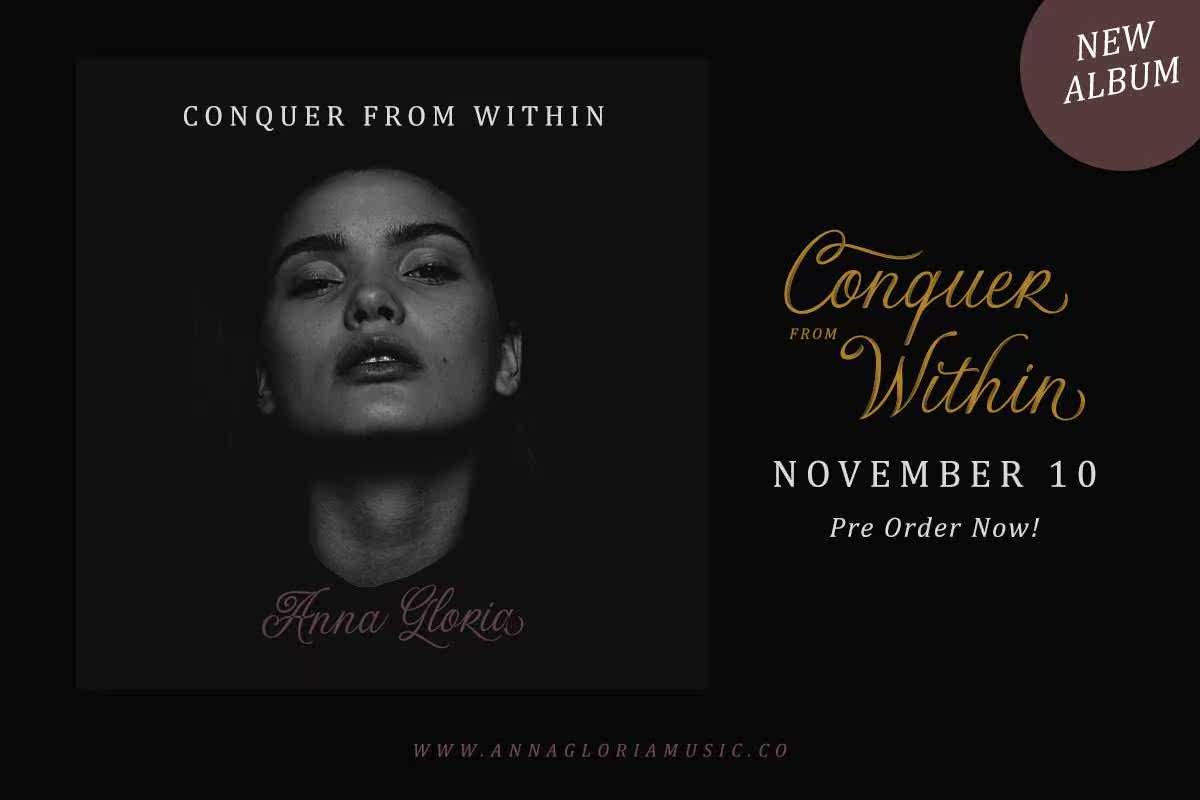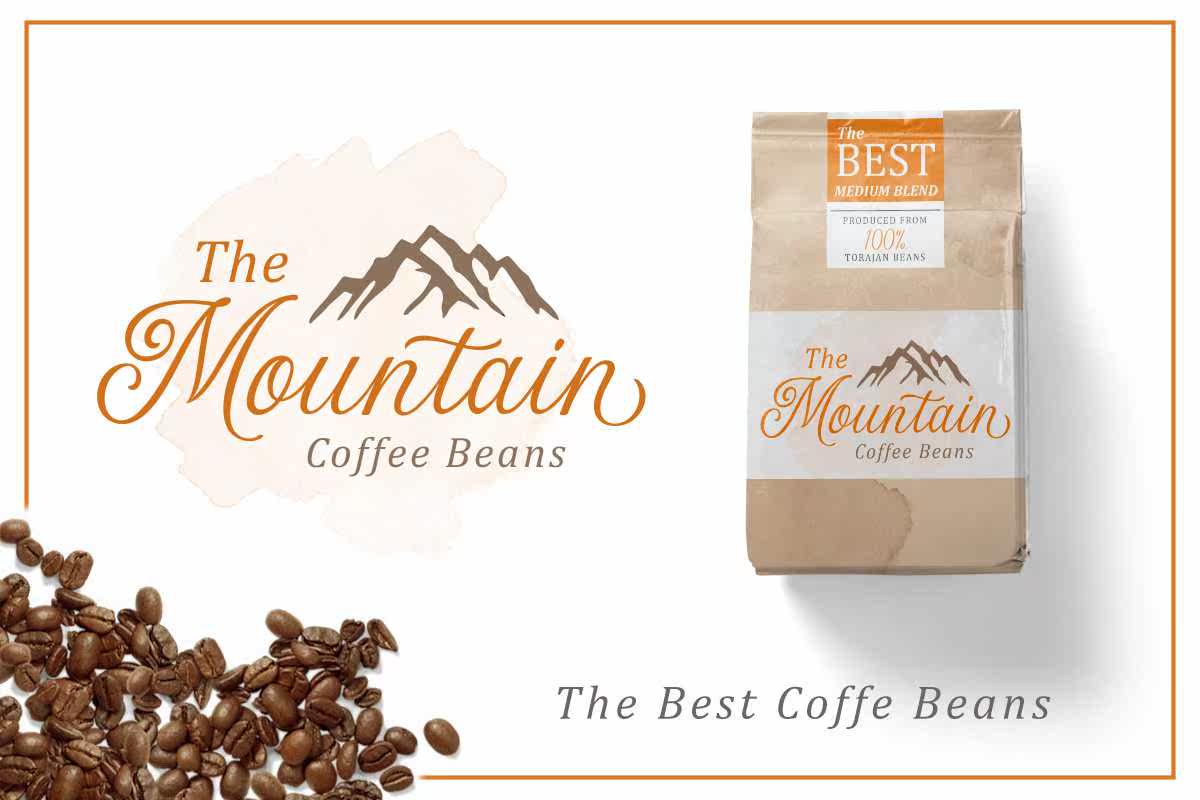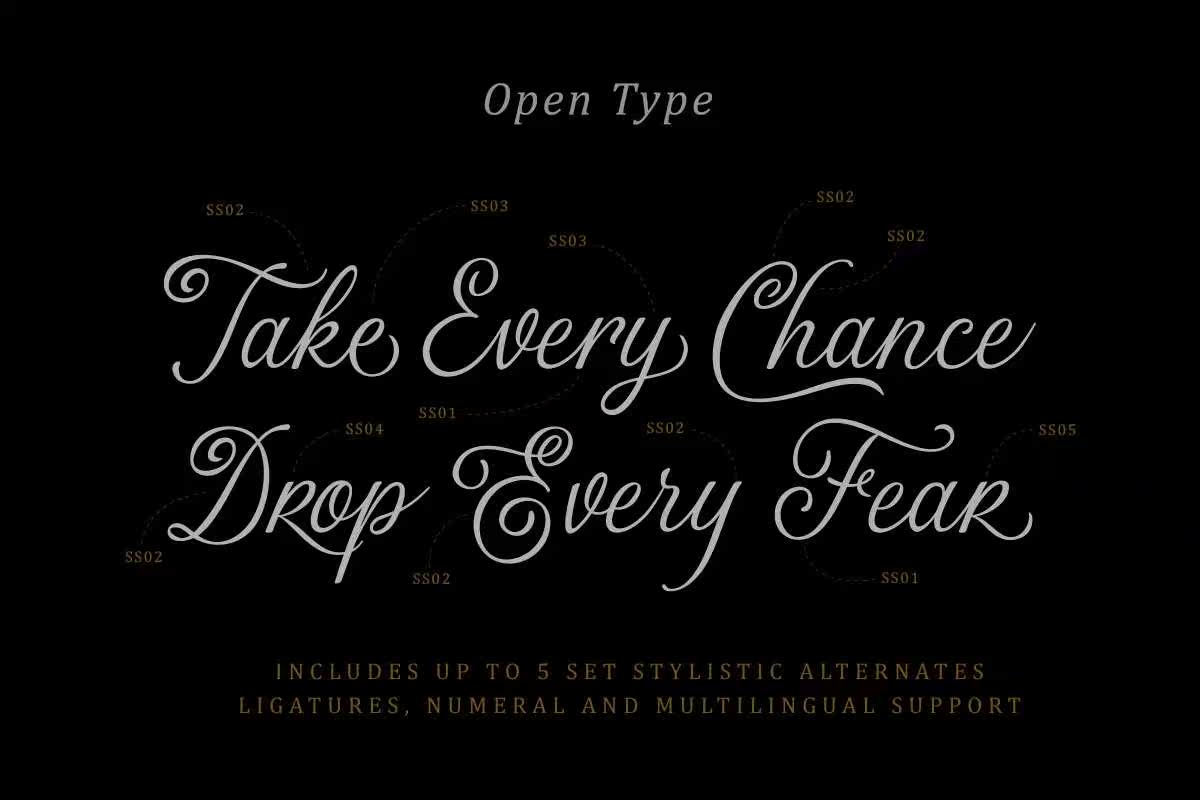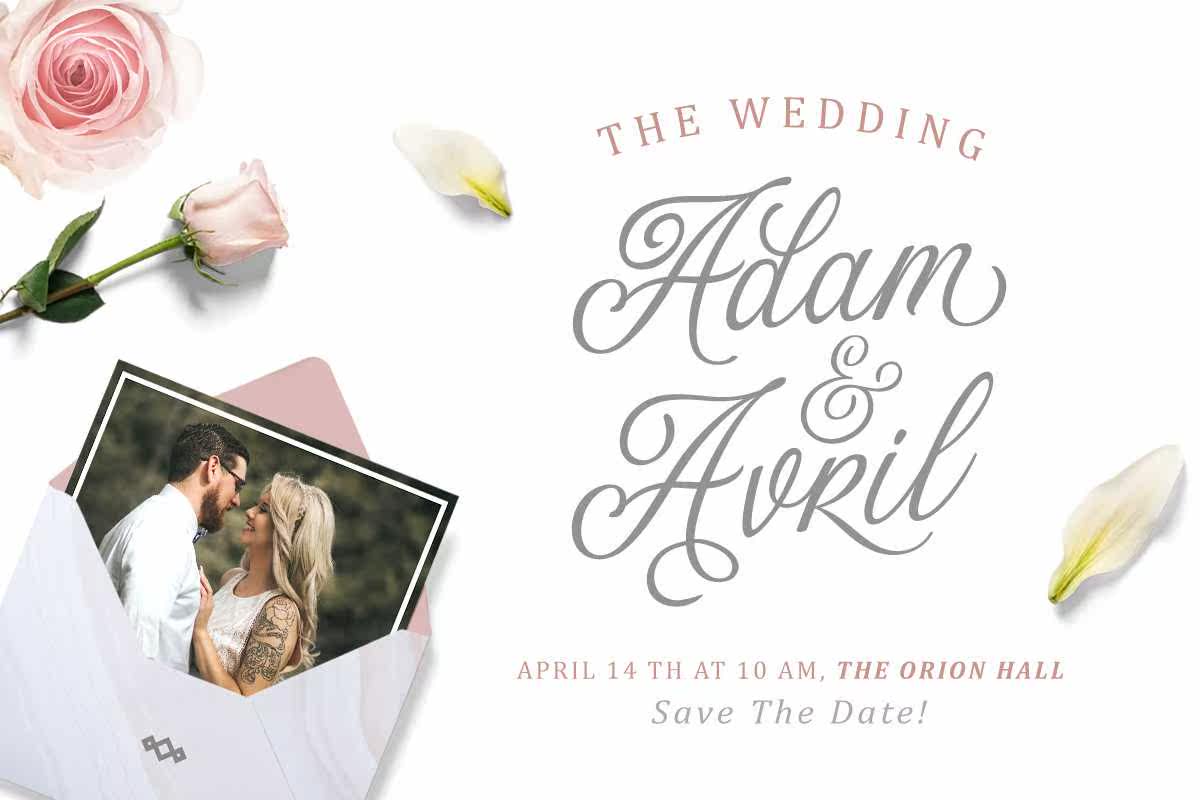
大多数脚本。aclassyscript,漂亮地流动并带来完美的感觉。此字体适用于EUSEDASTSHIRT设计、徽标/品牌、签名、标题、字母引号等。它还包括大写、小写、标点符号、符号和数字、文体设置、替换、连字、,EtcalSo支持多语言。多数脚本。Aclassyscript可漂亮地流动并带来丰富的体验。此字体适用于EUSEDASTSHIRT设计、徽标/品牌、签名、标题、字母引号等。它还支持大写、小写、标点符号、符号和数字、样式集替换、连字等多语言。